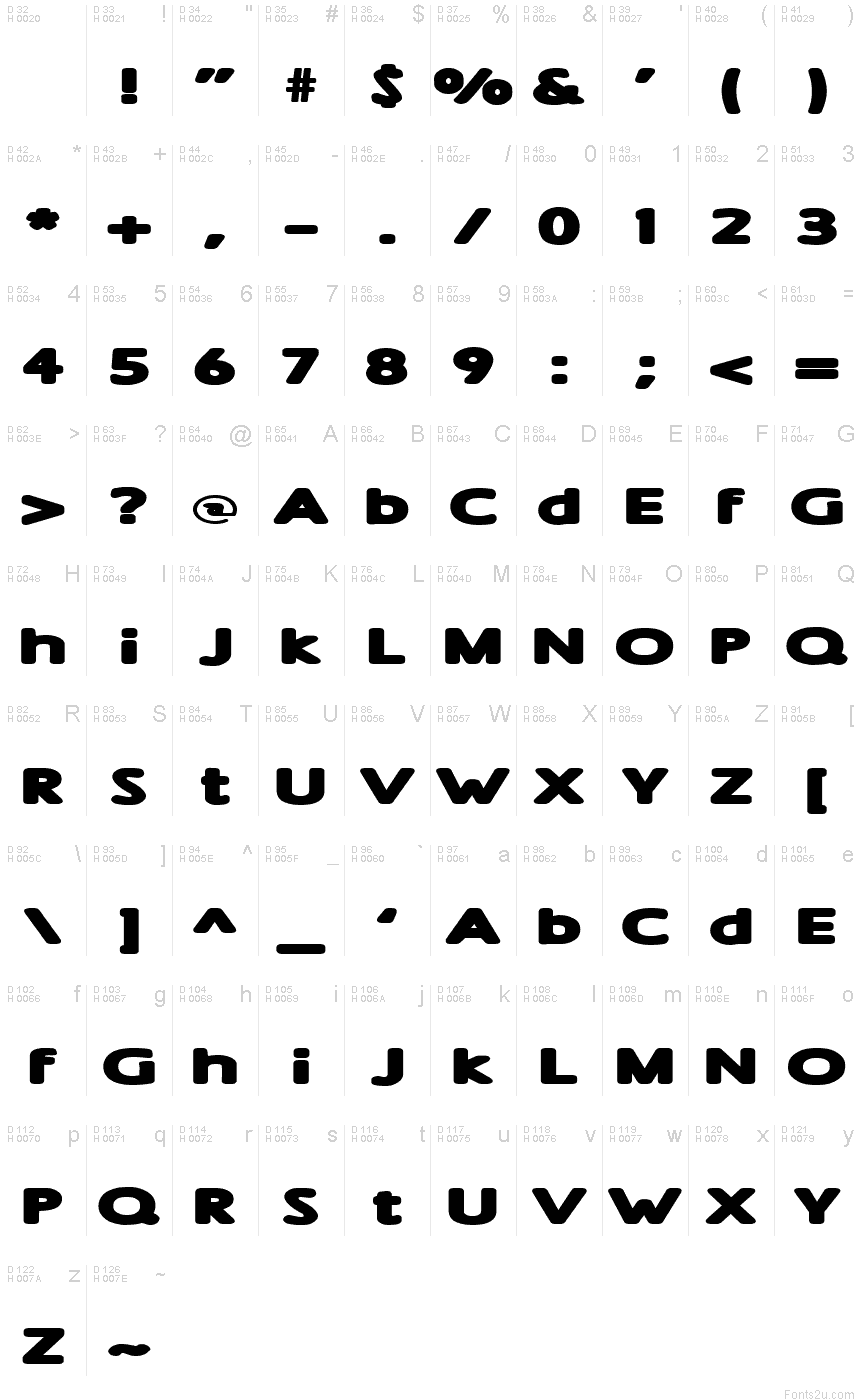
Sham Extra Bold di Ray Larabie è un font sans serif ultra-bold e arrotondato, gratuito, del 1996, dal carattere morbido e gonfio che punta più alla giocosità che al rigore geometrico. Le lettere sono ampie e compatte, con curve corpose, raccordi netti e un ritmo solido che conferisce vivacità anche alle forme più semplici.
Si adatta perfettamente a poster, brand per l'infanzia, packaging di snack, grafiche in stile arcade e titoli di riviste di impatto, dove questo font gratuito riesce a dare peso a poche parole. Usalo per titoli brevi, schermate di titoli, loghi o iniziali quando vuoi forme spesse e angoli arrotondati per trasmettere un messaggio amichevole anziché austero.